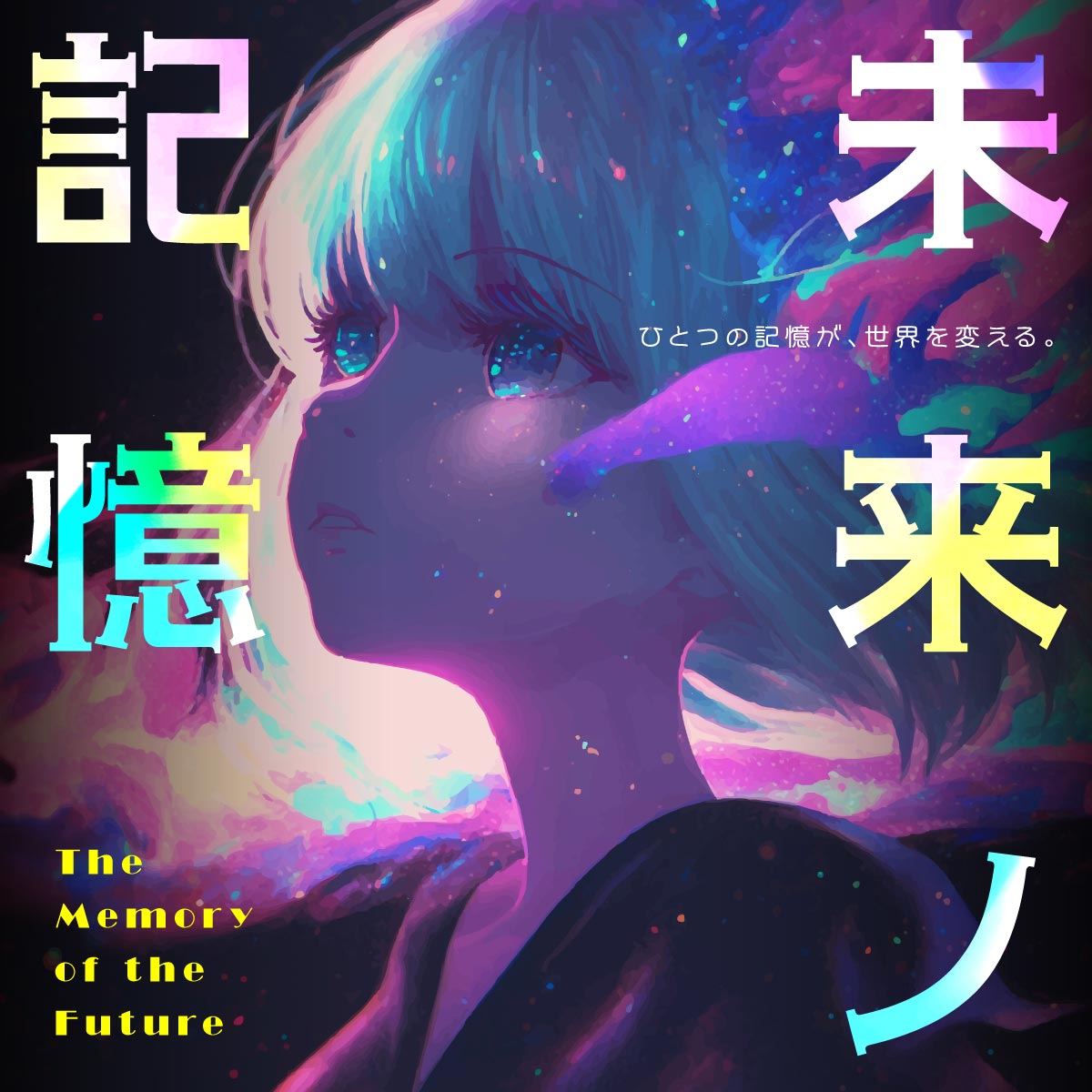
和文・欧文45書体セット
タイトル・見出しの表現力を高める! 和文・欧文 45書体セット
タイトルや見出しに最適な表現力を持つ和文・欧文45書体を厳選した特別セット
使用例
和文メイン手書き風
使用フォント:AFSてがき・AFLetter・AF-WelcomeBoard4
和文・欧文デザイン書体
使用フォント:AFSセリフゴシック04 E、AFSテンドゥ04 R、AFSBroadway
欧文メイン焚火
使用フォント:AFSBroadway・AFSFutuM
収録書体一覧
テロップ専用和文フォント AF-テロップミンフォーマル
加工フォントシリーズ (斜体/扁平/長体) に同梱されている「AFSミンフォーマルE (AFSMinformalE.ttf)」の縦線をさらに太くし独立しました。
AF-ユニバーサルビュー 4書体セット
AF-ユニバーサルビュー L・R・DB・E をまとめた4書体セット。
AFSまるご風 10書体セット
AFSオリジナルフォント35書体から10書体を厳選し丸ゴシック風の加工を施しました。
AF-ss04U
AF-ssの字形デザインは、縦線、横線に太さ細さの強弱を付け字体そのものに強い印象を与えました。
AFNewSelifGothic04E
欧文のエジプシャン書体に近いデザイン。JISX0213の1990字形と2004字形の2製品ご用意しており、本製品はその2004字形版 (例えば「つじ」のしんにょうは、点2つ) です。
AFNewFlora04U_CP932
AFNewFlora04U_CP932は、モダンな横太丸ゴシック体と篆書を組み合わせた独特なブレンド書体。個性的でやわらかいイメージに仕上げました。可愛らしさもありファッション誌へのキャプションやテロップなど幅広く使えるディスプレイタイプです。
AFSテンドゥ04R
篆書体をベースにしつつ仮想ボディを正方形に変更し、横組みにも適したモダンなデザインに仕上げられています。大見出し小見出しといったアイキャッチ用としてご利用ください。
AFSてがきフォント 6書体
日本人がペン字として使う行書体に楷書系の癖を加味した普段使いなリアル書体です。
AFS復刻欧文フォント AFSTRoman
1932年スタンレー・モリスンによるタイムズニューローマンが新聞書体となる以前(旧タイプ)のタイムズ・オールド・ローマンの復刻。
AFS復刻欧文フォント AFSBo
ジャンバチスタ・ボドニ制作の復刻。直線や円弧を使ったローマン体で縦横の線の太さを大きくコントラストをはっきりさせた見出し用に最適な書体。
AFS復刻欧文フォント AFSGara
16世紀ごろクロード・ギャラモンによるオールド・ローマン体の復刻。エックスハイトは高く、数字も上下が揃うデザインが特徴。
AFS復刻欧文フォント AFSCloisB
1914年モーリス・フラー・ベントンによるオールドローマン体、クロイスターボールドの復刻。
オールマイティな欧文 AF22CENTURY
見慣れたデザインで読みやすく、リーフレットやお洒落なドキュメントに最適。個人同人向けアニメ、動画向けなフォント。
アイキャッチ AFSelifE 欧文フォント
アイキャッチ用としてキーワードなどにお使いください。
AFS復刻欧文フォント AFSFutuM
1924年パウル・レンナーによるフーツラ・グロテスク(サンセリフ体)の復刻。細めの明るいデザインが特徴。
復刻欧文 AFSNeuSansR
AFSNeuSansのウエイトをLクラスから少し太くしRに改版しました。何処にでも違和感なく使える便利な本文用書体です。
AFS復刻欧文フォント AFSGillS
1926年ごろエリック・ギルによるギルサンの復刻。